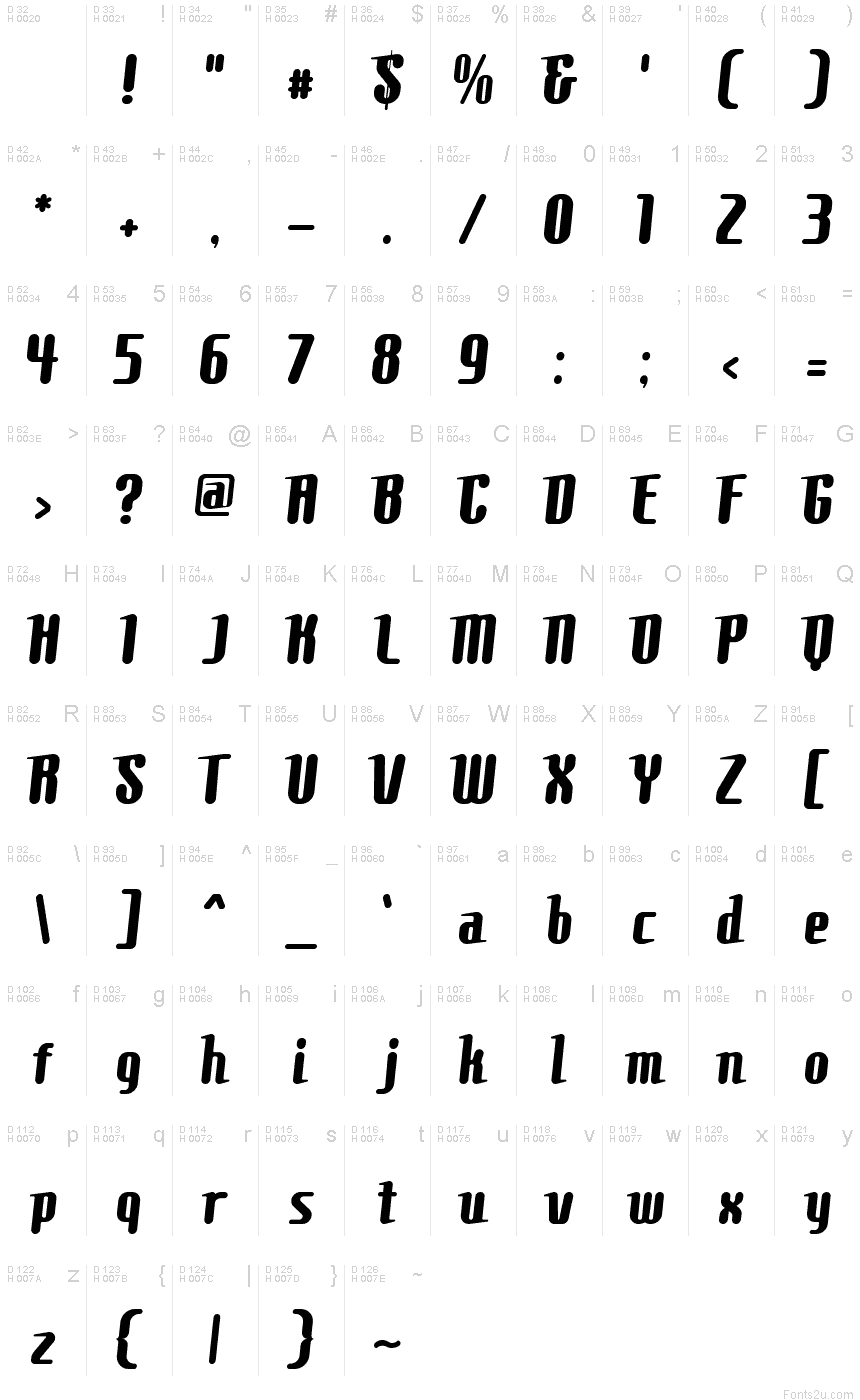
Comons Bold autorstwa Masayo Shimojimy to darmowy krój pisma typu slab serif w stylu retro, wyróżniający się pewnym, energicznym nachyleniem. Grube pociągnięcia, zwarty rytm i subtelnie zaokrąglone górne krawędzie nadają mu wyrazisty, „atramentowy” charakter, który przykuwa wzrok, pozostając jednocześnie czytelnym na pierwszy rzut oka. Użyj go w dużym rozmiarze, aby wyeksponować odważne sylwetki liter, a w tekście pomocniczym zrównoważ go lekkim, neutralnym krojem bezszeryfowym.
Za pomocą Comons Bold stworzysz przyciągające wzrok plakaty, logotypy, etykiety produktów, opakowania w stylu vintage, mocne nagłówki oraz grafiki do mediów społecznościowych, które wymagają natychmiastowego efektu. Solidne formy zapewniają czytelność liter nawet wtedy, gdy napis jest przycięty lub nałożony na teksturę, dzięki czemu ten darmowy font świetnie sprawdza się w złożonych layoutach. Aby dodać mu jeszcze więcej charakteru, spróbuj zastosować większe odstępy między literami w dużych rozmiarach, co pięknie wyeksponuje jego rytmiczne, wyrzeźbione krzywizny.